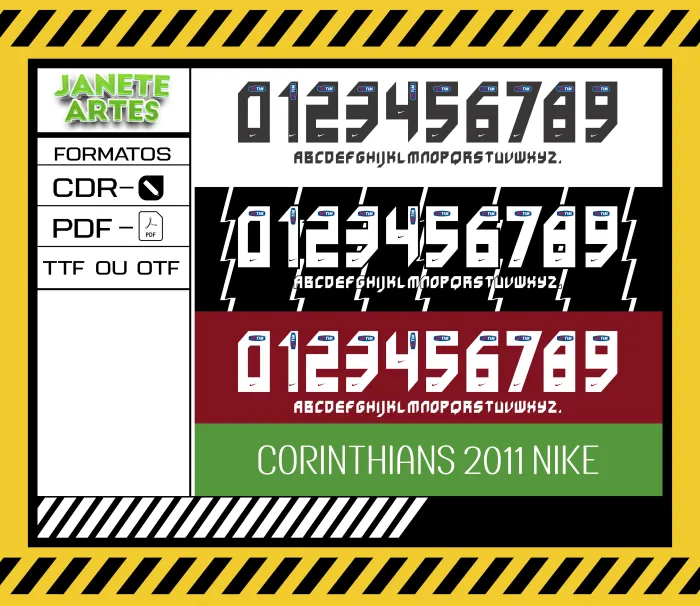
Fonte de Time Tipografia Corinthians 2011
Uma história de paixão e estilo no futebol
Imagine a emoção de um torcedor apaixonado que quer expressar seu amor pelo Corinthians não apenas no estádio, mas também no visual do dia a dia. Foi assim que nasceu a ideia do Arte Fonte de Time Tipografia Corinthians 2011 para Camiseta. Inspirado na tipografia usada pelo time no ano de 2011, o design traz uma conexão forte com a história vitoriosa e a identidade da torcida. A criação desse arquivo digital oferece a chance de personalizar camisetas que carregam essa energia, unindo estilo e paixão de forma única.
- Design fiel à fonte de tipografia usada pelo Corinthians em 2011
- Combine a fonte com números e nomes dos jogadores para um visual completo
Com o Arte Fonte de Time Tipografia Corinthians 2011 para Camiseta você transforma sua paixão pelo Corinthians em peças exclusivas, cheias de identidade e estilo. Aproveite essa chance de criar algo único para você ou para sua turma de torcida!